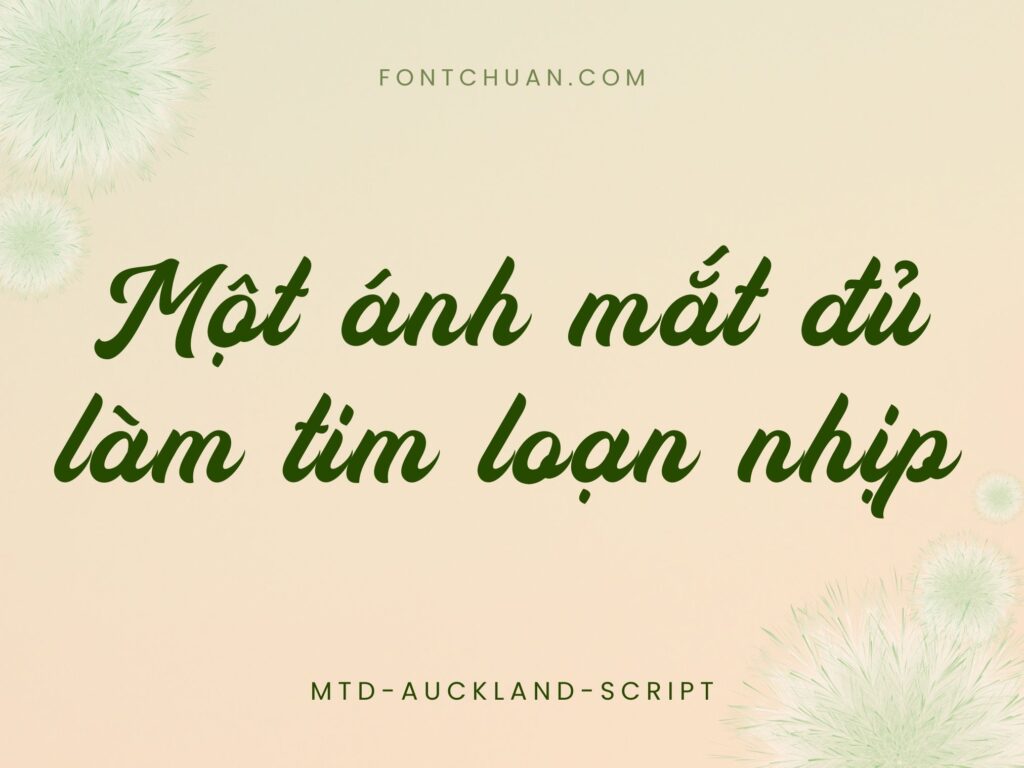
Font Auckland Script là một kiểu chữ viết tay đậm nét với phong cách vintage, được thiết kế bởi Sarid Ezra và phát hành vào năm 2017. Với các đường nét uyển chuyển và tinh tế, Auckland Script mang lại sự thanh lịch và độc đáo cho các thiết kế.
Phiên bản Auckland Script đã được Việt hóa bởi Mộc Hạ, hỗ trợ đầy đủ tiếng Việt cùng hơn 64 ngôn ngữ khác như Anh, Pháp, Tây Ban Nha, Đức và Ý, mở rộng khả năng ứng dụng trong thiết kế đa ngôn ngữ. Font này đã được thành viên Font Chuẩn sưu tầm và chia sẻ, đáp ứng nhu cầu của cộng đồng thiết kế. Với thiết kế bao gồm các ký tự viết tay mềm mại, 5 bộ ký tự thay thế, ligatures, swash và gạch chân, Auckland Script phù hợp cho các ứng dụng như thiết kế logo, thiệp mời, bao bì sản phẩm và các ấn phẩm quảng cáo. Các ngành nghề như quảng cáo, giáo dục, công nghệ và ẩm thực có thể tận dụng font này để tạo ra thiết kế ấn tượng và thu hút.